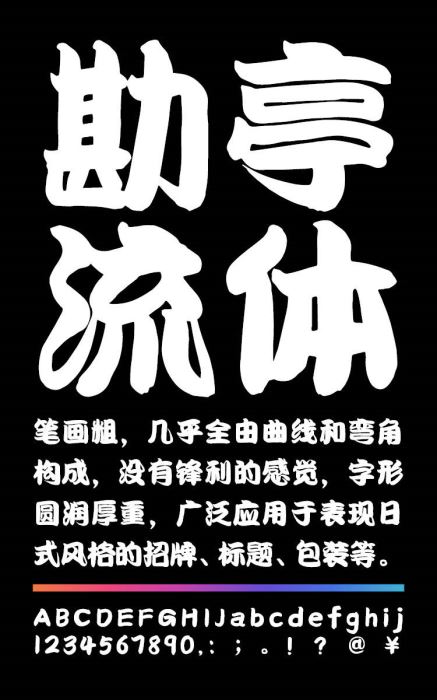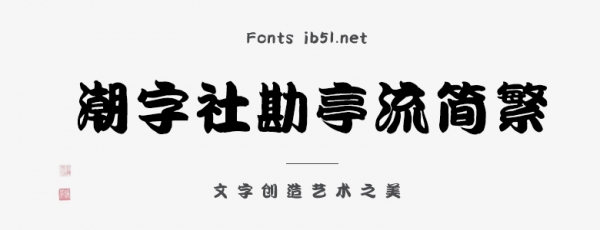
潮字社勘亭流簡繁-閃一款由銳字潮牌字庫出品的藝術字體,這款字體筆觸粗實,幾乎全由曲線和彎角構成,沒有鋒利的感覺,字形圓潤厚重,適合應用于藝術設計、平面宣傳設計、網頁設計,書法字帖等領域,需要的朋友可以前來本站下載。
潮字社勘亭流簡繁,是潮字社品牌字庫旗下的一款字體。銳字潮牌字庫擁有本字體獨家版權,筆畫粗,幾乎全由曲線和彎角構成,沒有鋒利的感覺,字形圓潤厚重,廣泛應用于表現日式風格的招牌、標題、包裝等